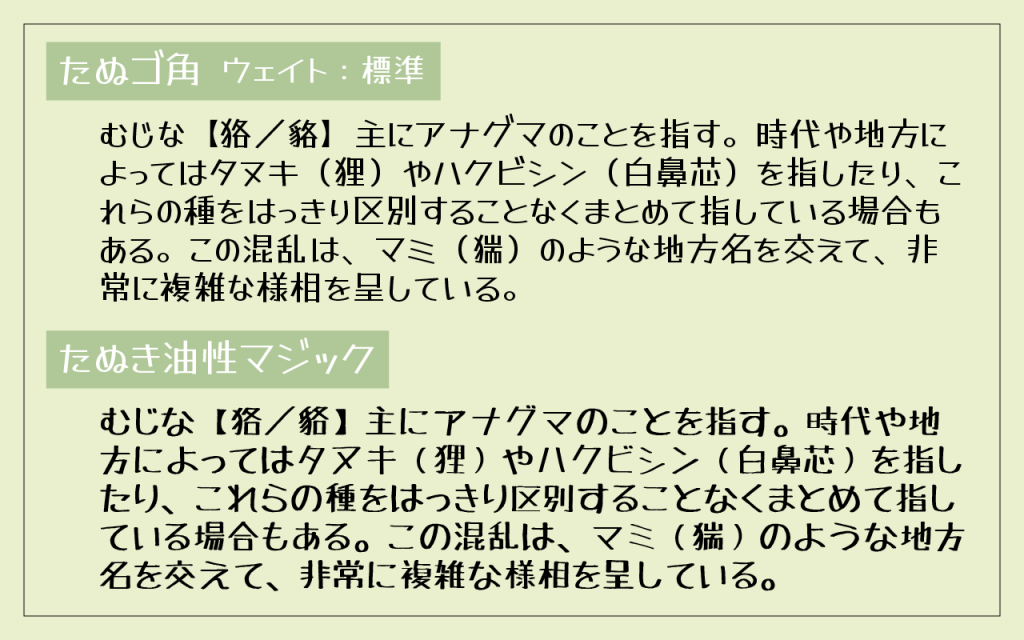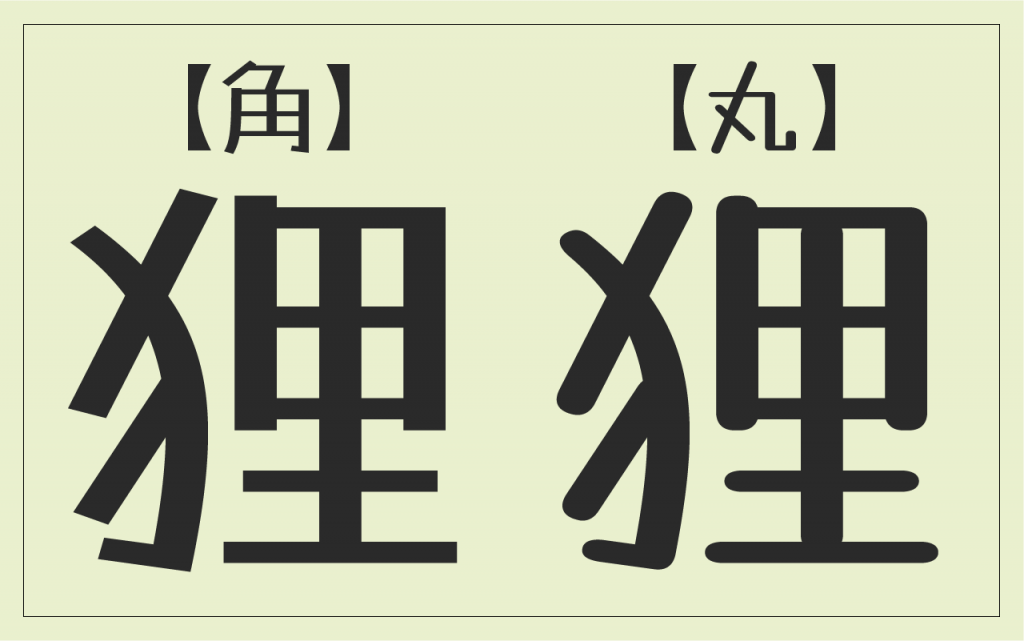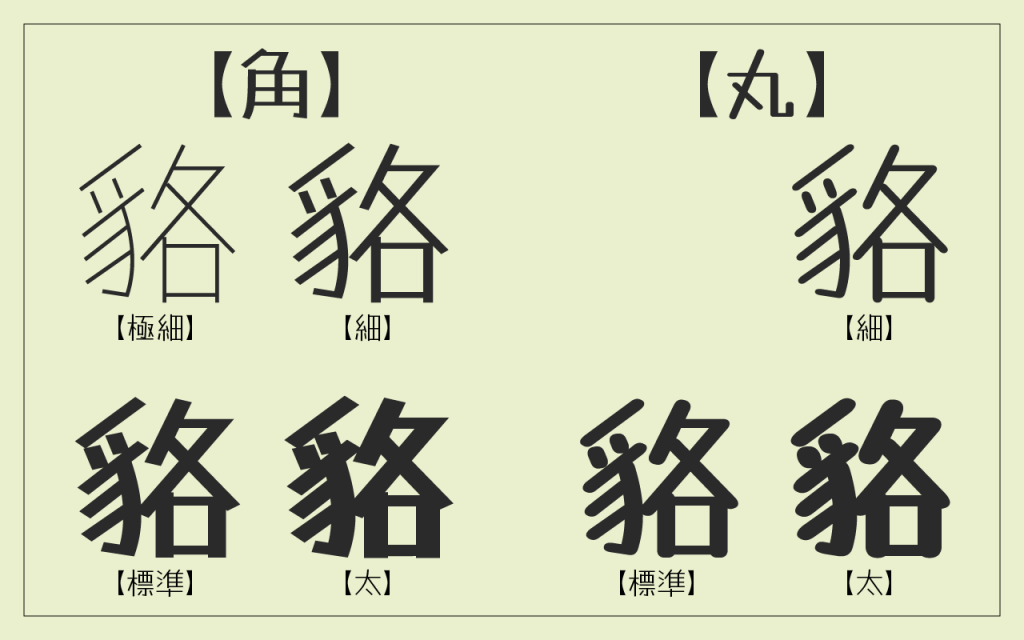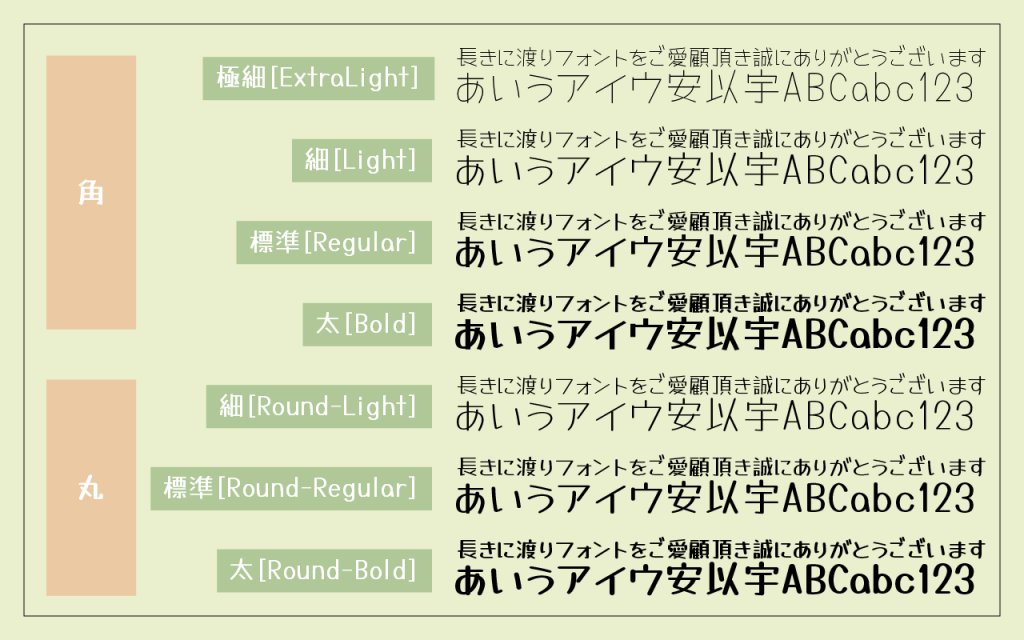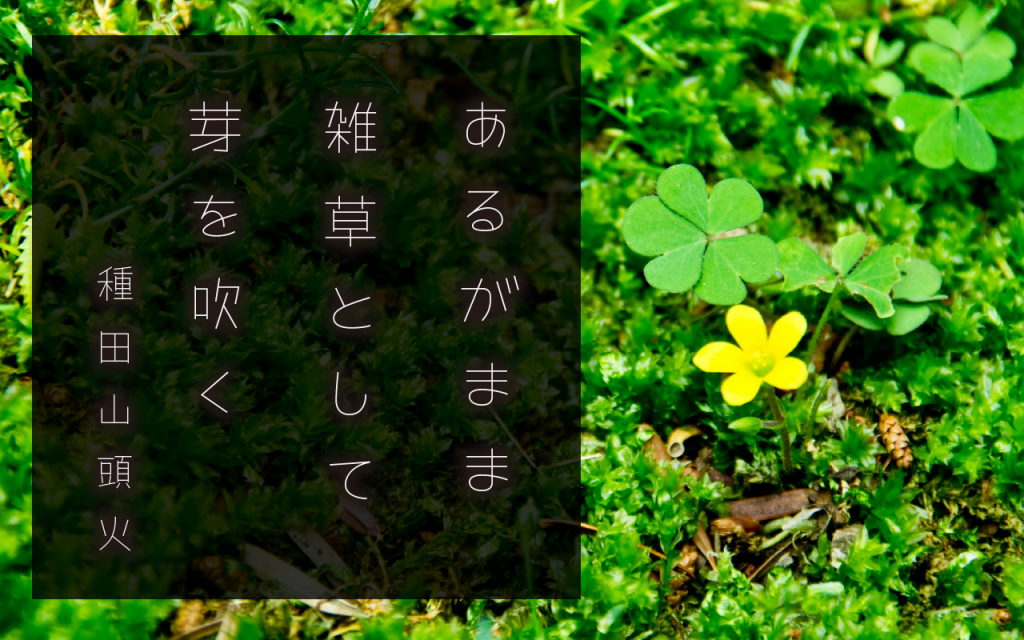
『たぬゴ』とは
当サイトで公開しているフリーフォント『たぬき油性マジック』のリニューアル版フォントとして作成したフォントです。
前作『たぬき油性マジック』の特徴である親しみやすさをキープしつつ、さらに使いやすく・読みやすく、かわいいタイプデザインを目指して作成したフォントです。
『たぬゴ』は、Google Fonts から支援を受けて作製したフォント『Yusei Magic』に、新たにLightウエイトや角グリフを追加して作成しています。
収録グリフ
ひらがな・カタカナ・英数字・記号、JIS第二水準までの漢字及びシフトIBM拡張漢字(計7,000文字以上)を収録しています。
- 半角英数字、基本ラテン文字、キリル文字、ギリシャ文字など
- ひらがな、カタカナ、全角英数、全角記号など
- 漢字(JIS第一水準、JIS第二水準、IBM拡張文字)
デザイン・ウェイト
画の端が角張ったデザインの『たぬゴ角』と、丸みを帯びたデザインの『たぬゴ丸』の2種類を用意しました。
また、『たぬゴ角』は極細・細・標準・太(ExtraLight・Light・Regular・Bold)の4ウェイト、『たぬゴ丸』は細丸・標準丸・太丸(Light・Regular・Bold)の3ウェイトを用意しています。